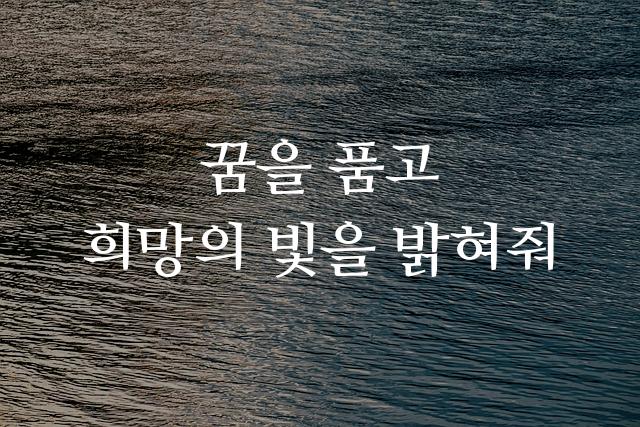
전주공예고딕체는 전통과 현대가 조화를 이루는 고딕체 폰트로, 깔끔하고 읽기 쉬운 특징을 갖추고 있습니다. 모던한 감성이 돋보이며, 다양한 디자인에 유연하게 적용될 수 있습니다.
전주공예고딕체은(는)
기본 고딕, 감성적인, 부드러움 계열의 생김새를 가지고 있으며
로고 디자인, 초대장, 제품 포장 등에서 자주 활용되며, 효과적인 메시지 전달에 적합합니다.
이 폰트는 패션/뷰티, 문화/예술, 건축/인테리어 분야에 잘 어울리며,
세련된, 예술적인, 고급스러운 느낌을 담고 있는 것이 특징입니다.